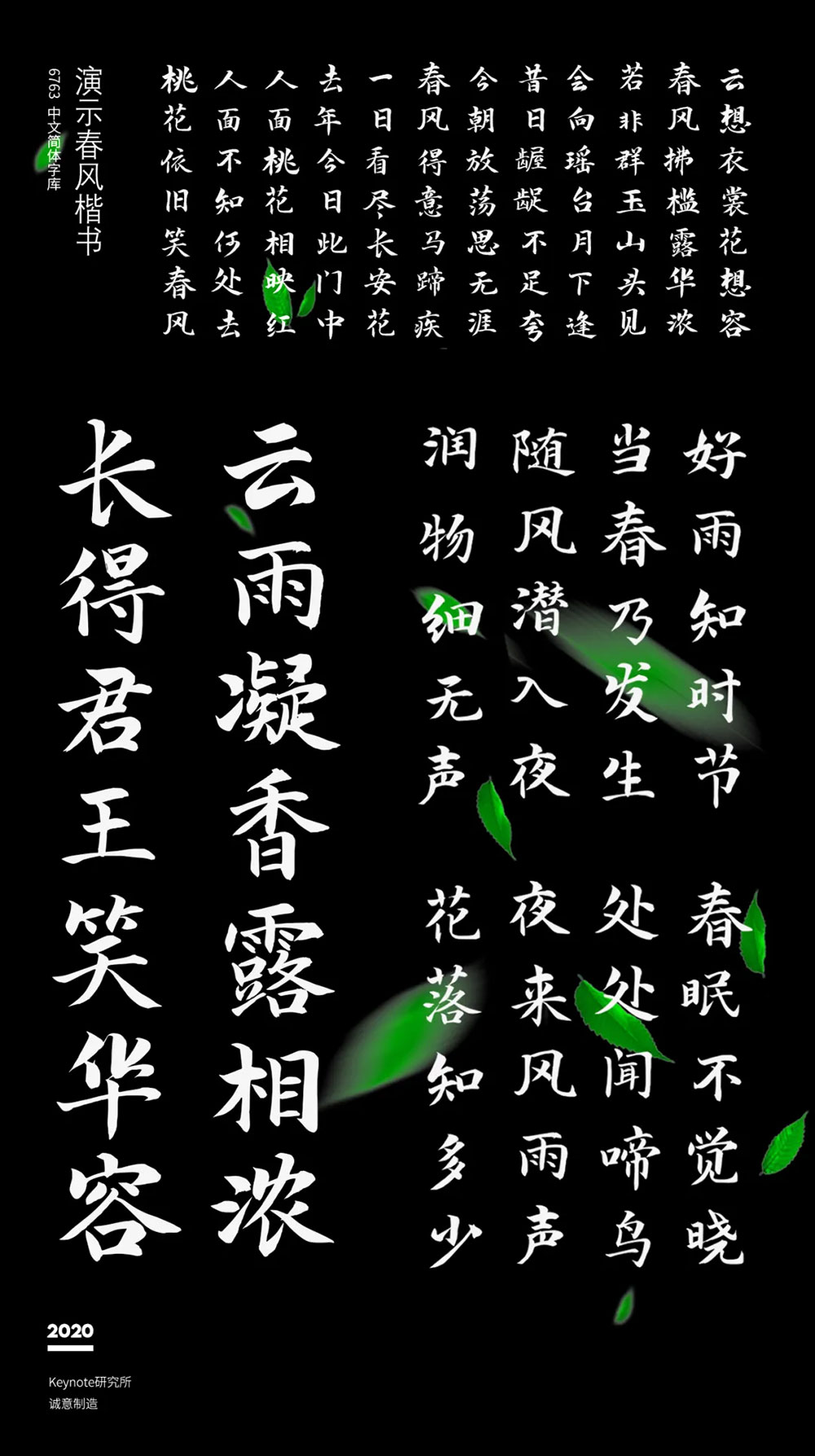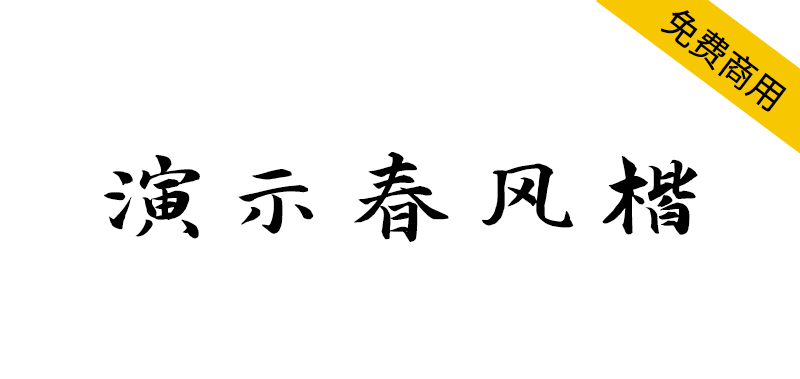
【演示春风楷】适用于幻灯片演示的免费商用字体
你好,这里是 Keynote研究所,我是人生哥。设计,重要的是,如何解决用户所面临的当前问题,两年前,为了解决在 Keynote 中文字不能倾斜的问题,我做了一次大胆的尝试:自己动手改造出一款 Keynote 可用的倾斜字,让幻灯片设计师可以在Keynote中一键倾斜文字。于是基于对谷歌开源字体「思源黑体」的倾斜处理,便有了 —演示斜黑体。但很多人说,这款字应该叫做演示斜杠体,因为是它,让关于我的故事不再是只有PPT,又加上了一道斜杠——字体。
优秀幻灯片,集巧妙的逻辑编排与可视化图形语言于一身,使原本枯燥的内容,变得更加易懂且利于表述,甚至可以引起大范围传播。发展到今天,PPT 已经不局限于“大字报工具”,它更像是一个多媒体容器,集合了图形语言、图标元素、风格字体、图片视频、3D模型·········从“实用为先”到兼顾“策略与颜值”的双重美学。甚至,它已为很多人创造了就业机会,当然也包括我。